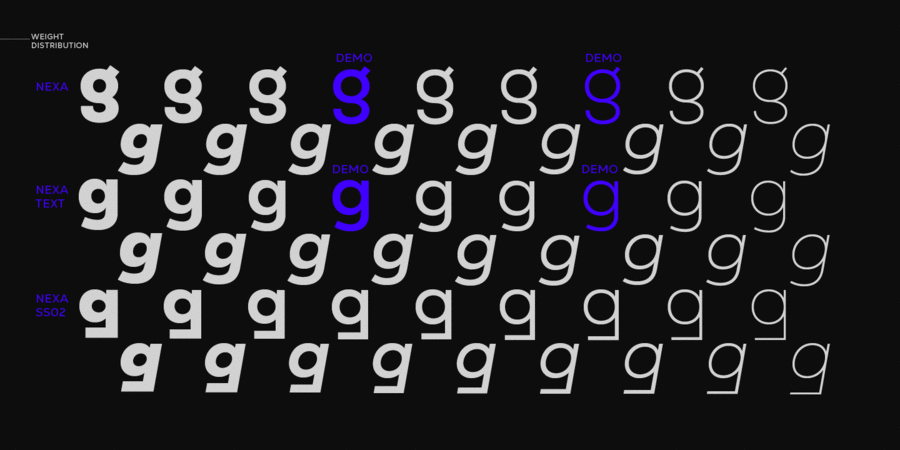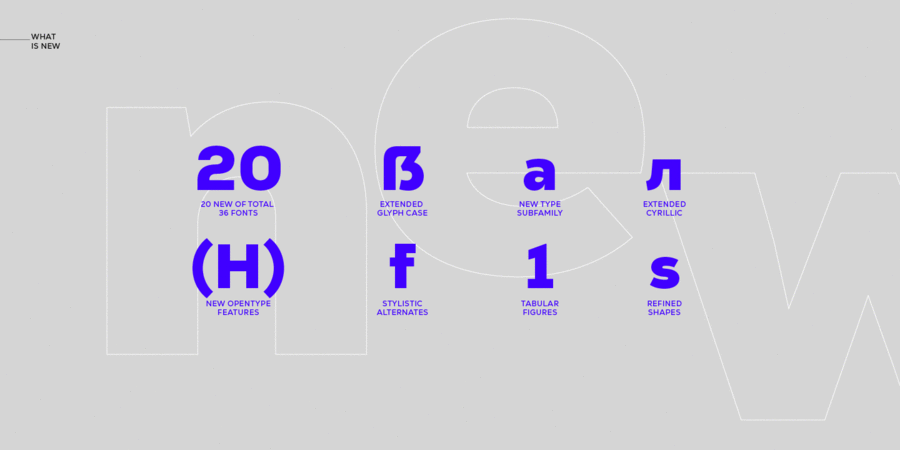
Оновлене сімейство шрифтів Nexa підходить для заголовків будь-яких розмірів і текстових блоків як максимальної, так і мінімальної ширини і висоти. Повна гарнітура Nexa включає 9 ваг і 36 шрифтів. Шрифти з сімейства Nexa пристосовані для будь-якого типу графічного дизайну цифрових, веб, друкованих, твердих поверхонь, тканин, а також плакатів, логотипів і брендингу. Ви можете скачати 4 безкоштовних шрифту Nexa – Nexa Bold, Nexa Light, Nexa Text Bold, Nexa Text Light. Оновлені можливості: Підтримка кирилиці; Болгарська локалізація; Нове підсімейство Nexa Text; Нове полегшене накреслення з відповідним курсивом; Стилістичний набір, адаптований до дисплея – ss02; Табличні цифри. Удосконалене сімейство шрифтів Nexa містить додаткову вагу Extra Light разом із курсивом, а також доповнення підсімейства – Nexa Text для довгих текстів, з додаванням ще одного футуристичного стилістичного набору. Таблиця гліфів включає покращену розширену латиницю та новий набір якісних локалізацій для кирилиці. Шрифт дуже функціональний та розбірливий завдяки багатьом можливостям OpenType, таким як чутливість до регістру, контекстно-залежні знаки та стильові налаштування. Оптимізований кернінг, вертикальни метрики, апроші, роблять верстку блискучою. Шрифт розроблений Светославом Сімовим у 2012-2020 роках.
Nexa підтримує 83 мовиУкраїнська, Англійська, Німецька, Польська, Португальська, Іспанська, Французька, Російська, Чеська, Голландська, Італійська, Шведська, Турецька, Фінська, Білоруська, Сербська, Болгарська, Естонська, Литовська, Албанська, Африкаанс, Баскська, Бретонська, Валенсаска, Galician, Гельська (Шотландська), Данська, Індонезійська, Ірландська, Ісландська (Win), Каракалпацька, Каталонська, Норвезька, Окситанська, Ретороманська, Самі Лулі, Тсванська, Узбецька (Лат.), Фарерська, фризька, Чаморро, Естонська (Win), Південносаамська, Албанська (Win), Угорська, Верхньолужицька, Карельська, Латвійська (Mac), Литовська (Mac), Маорійські (Mac), Молдавська (Лат.), Нижньолужицька, Румунська (Win), Словацька, Словенська, Туркменська (Лат.), Хорватська (Win), Естонська (Mac), Курдська, Латишська, Маорійські, Руминська, Абазинська, Аварська, Агульська, Адигейська, Даргинську, Інгуську, Кабардино-Черкеська, Кабардинська, Карачаєво-Балкарська, Кумицька, Лакська, Лезгинська, Македонську, Мордовсько-Мокшанська, Мордовсько-Ерзянська, Ногайська, Рутульська, Табасаранська, Татська, Цахурська, Чеченська Функції сімейства шрифтів NexaЗастосування гарнітури у верстці:
Асоціації з сімейством шрифтів NexaОсобистість і характер гарнітури:
мінімалістичний, чіткий, делікатний, чистий, легкий, прохолодний, свіжий, модний, тонкий, сучасний, лаконічний, ясний, рівний, якісний, невагомий, прозорий, логічний, точний, повітряний, скляний, дротяний, міський, статичний, популярний, худий, глобалізований, глобалістічний, крихкий, холодний, Простий, твердий, зрозумілий, доступний, елементарний, правильний, формальний, серйозний, стійкий, стабільний, самостійний, відповідальний, західний, діловий, спокійний, креслярський, інженерний, нейтральний, помірний, стандартний, невиразний, універсальний, розумний, байдужий, комфортний, зручний, обов'язковий, сильний, переконливий, урбаністичний, надійний, значний, солідний, важкий, важливий, мотивуючий, залізний, сталевий, грубий, впевнений, потужний, непомітний